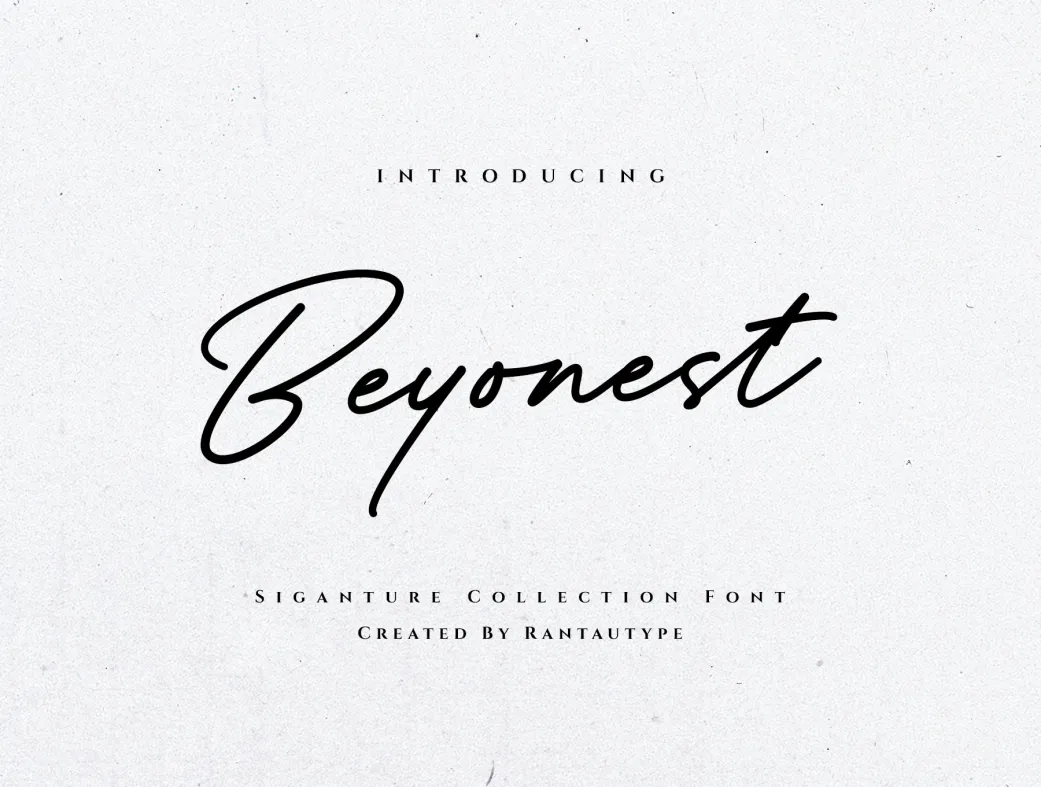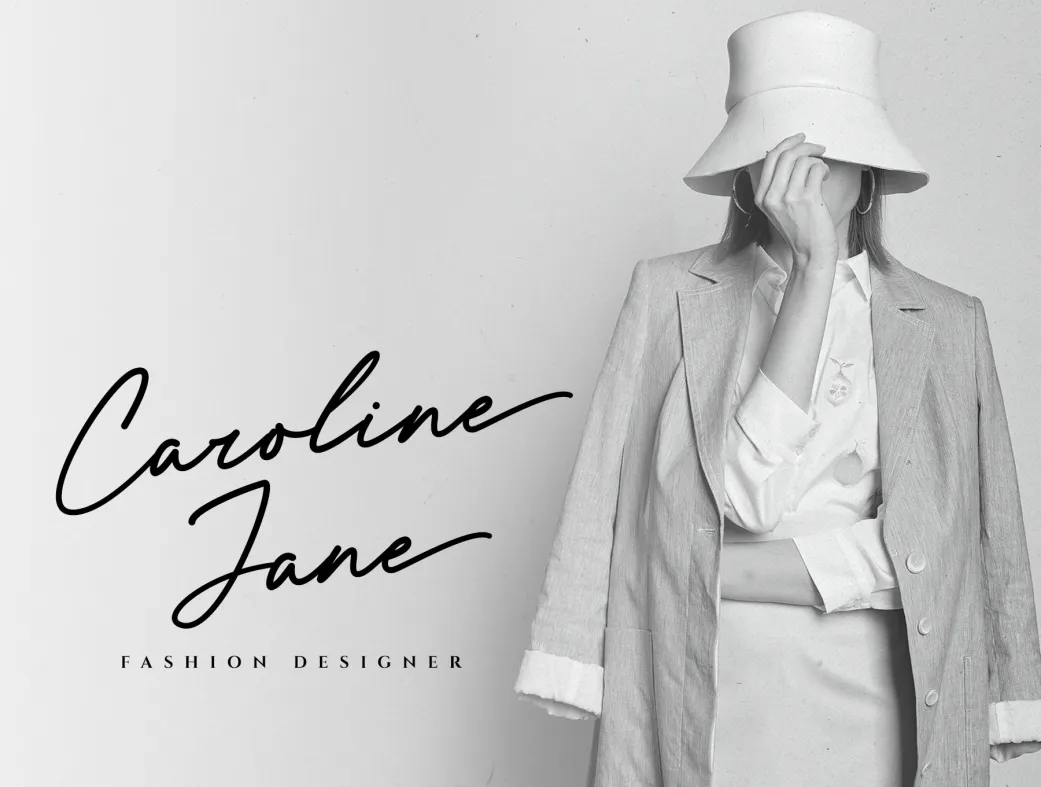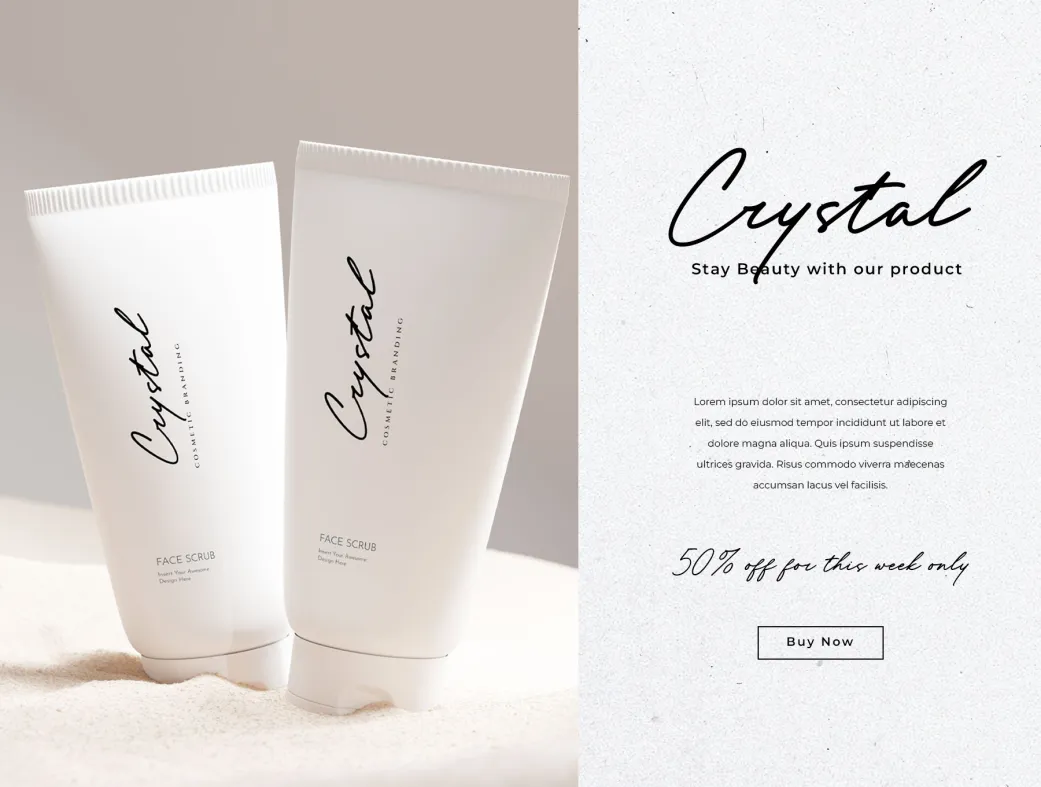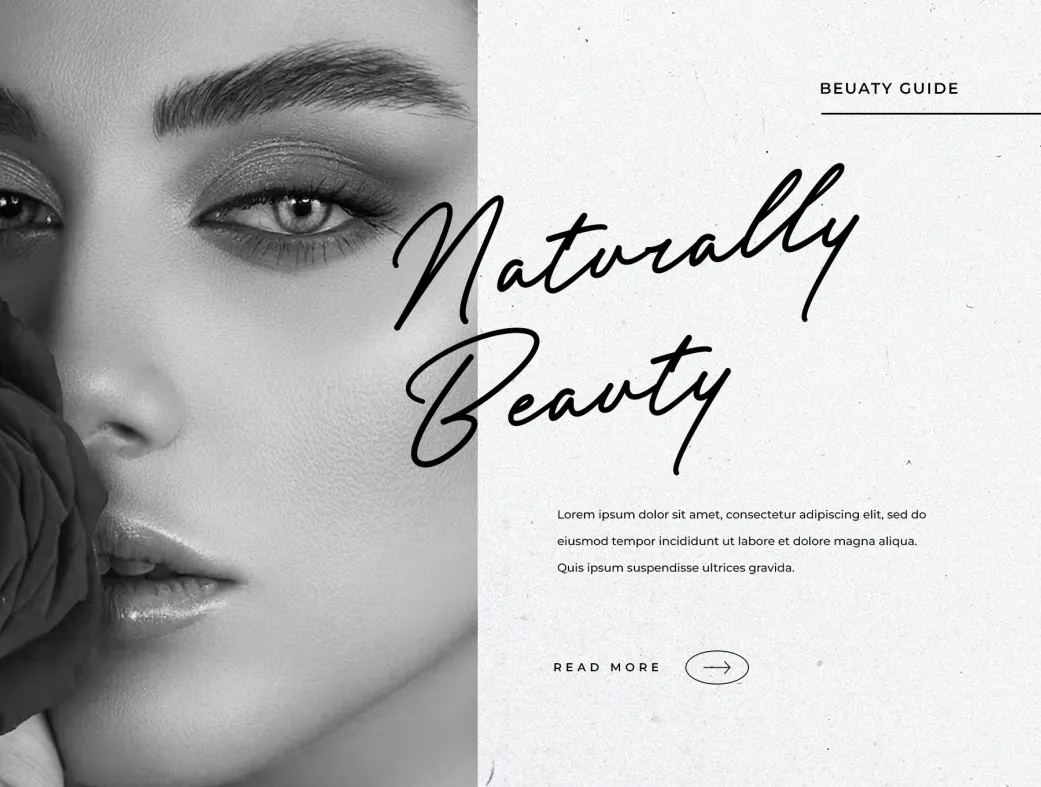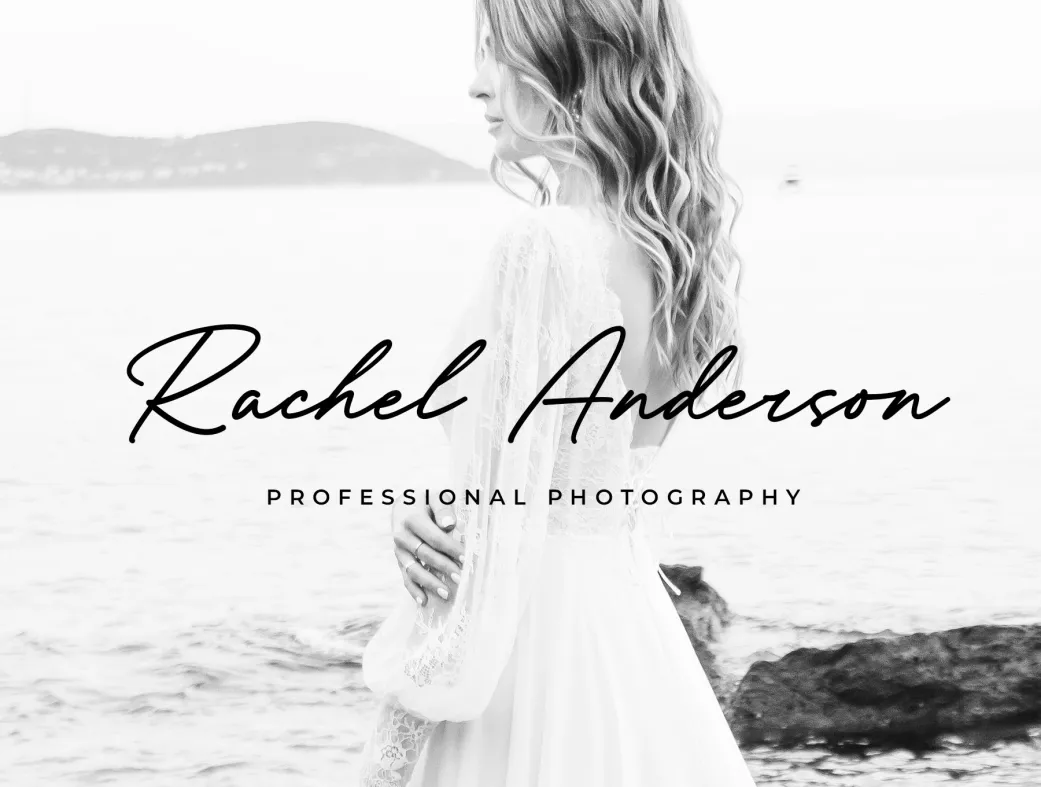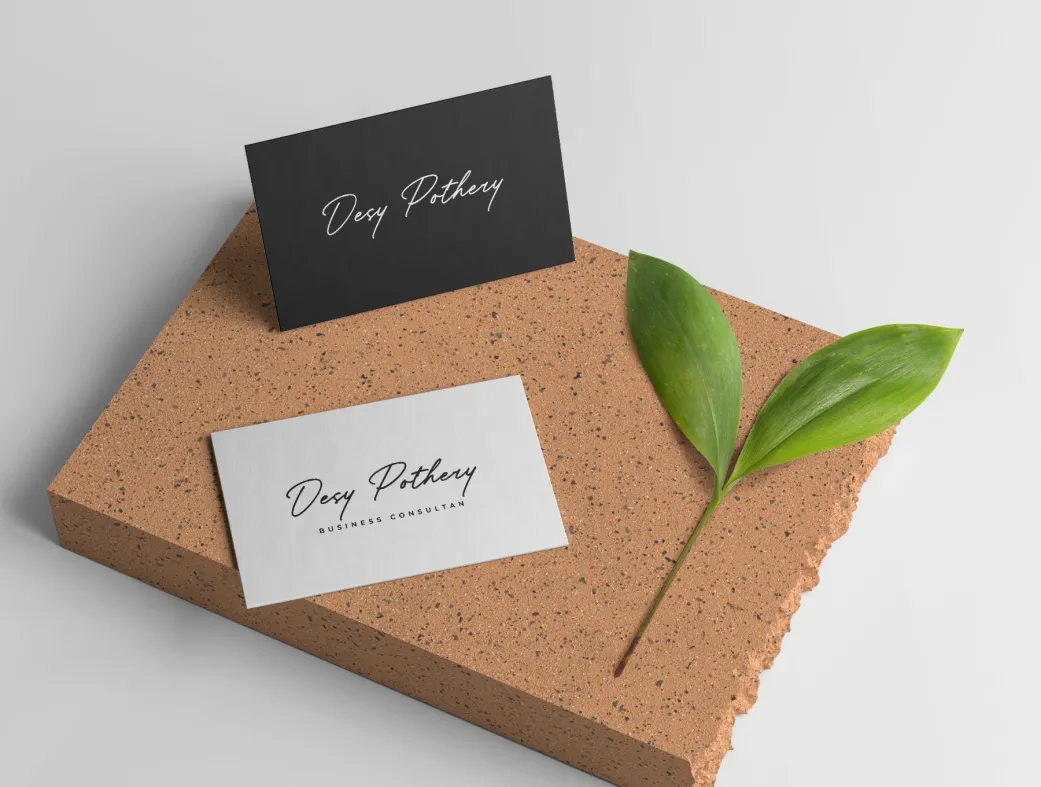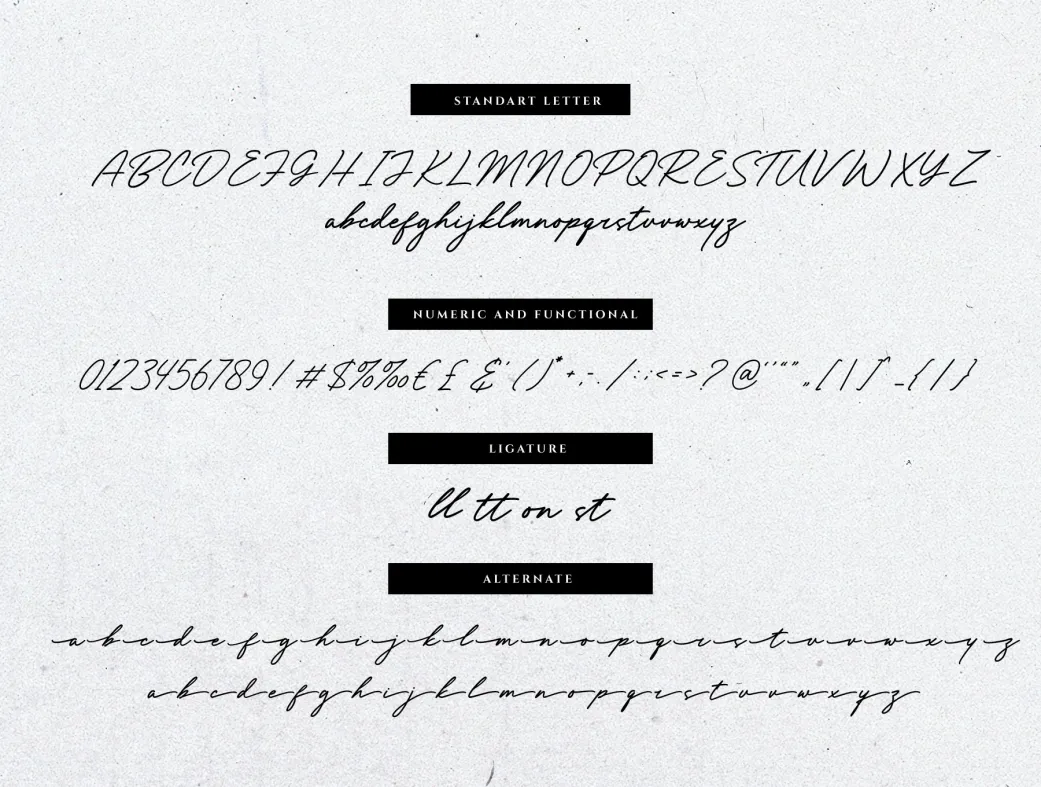
فونت امضا بادی بیونست | Beyonest
آیا به دنبال فونتی منحصر به فرد برای طراحی‌های خلاقانه‌تان هستید؟ فونت بیونست با طراحی شیک و مدرن، گزینه‌ای ایده‌آل برای هویت برند و پروژه‌های تجاری شماست!
Beyonest Bold Signature Font
فونت امضا بادی بیونست | Beyonest | Beyonest Bold Signature Font
معرفی محصول:
فونت امضا بادی بیونست (Beyonest) یک فونت خلاقانه و حرفه‌ای است که با طراحی نرم و طبیعی، قابلیت تطبیق با کاربردهای مختلف را دارد. این فونت مدرن و مینیمالیستی بوده و به شکلی زیبا و قابل‌خواندن طراحی شده است. با ویژگی‌های منحصر به فرد خود، بیونست گزینه‌ای ایده‌آل برای طراحان و برندها به شمار می‌آید.
ویژگی‌ها و مزایا:
فونت بیونست با حروف استاندارد A-Z و a-z، اعداد و کاراکترهای عملکردی عرضه می‌شود. این فونت شامل لیگاتور (Ligature) و حروف جایگزین (Alternate) است که به کاربران این امکان را می‌دهد تا طراحی‌های خلاقانه‌تری داشته باشند. همچنین، پشتیبانی از لهجه‌های چند زبانه، این فونت را به گزینه‌ای مناسب برای طراحان بین‌المللی تبدیل کرده است.
بیونست به دلیل طراحی شیک و جذاب خود، برای انواع پروژه‌های خلاقانه مانند لوگوها، عناوین، واترمارک‌ها در عکاسی، کاور، برندسازی، مجله‌ها، رویدادهای عروسی، نقل‌قول‌ها، کاور آلبوم، کارت ویزیت و پروژه‌های تجاری دیگر مناسب است. این فونت به راحتی می‌تواند هویت برند شما را ارتقا دهد.
کاربردها و نکات استفاده:
سوالات متداول:
1. آیا فونت بیونست پشتیبانی از زبان‌های مختلف دارد؟
بله، این فونت از زبان‌های متعددی مانند انگلیسی، اسپانیایی، فرانسوی و بسیاری دیگر پشتیبانی می‌کند.
4. آیا در فونت بیونست حروف جایگزین وجود دارد؟
بله، فونت بیونست دارای حروف جایگزین و لیگاتور است که به شما کمک می‌کند طراحی‌های خلاقانه‌تری داشته باشید.